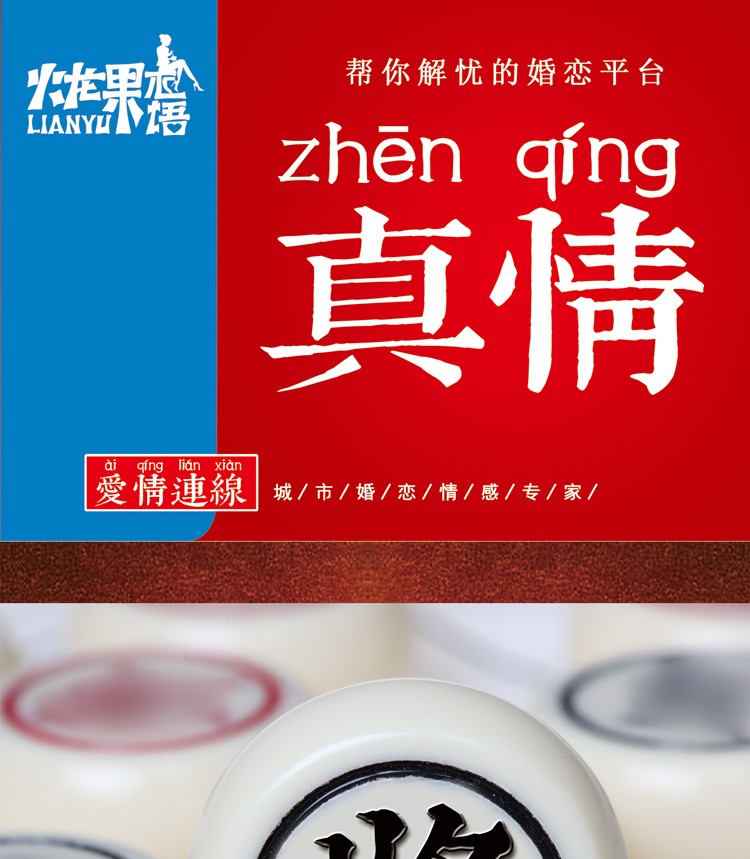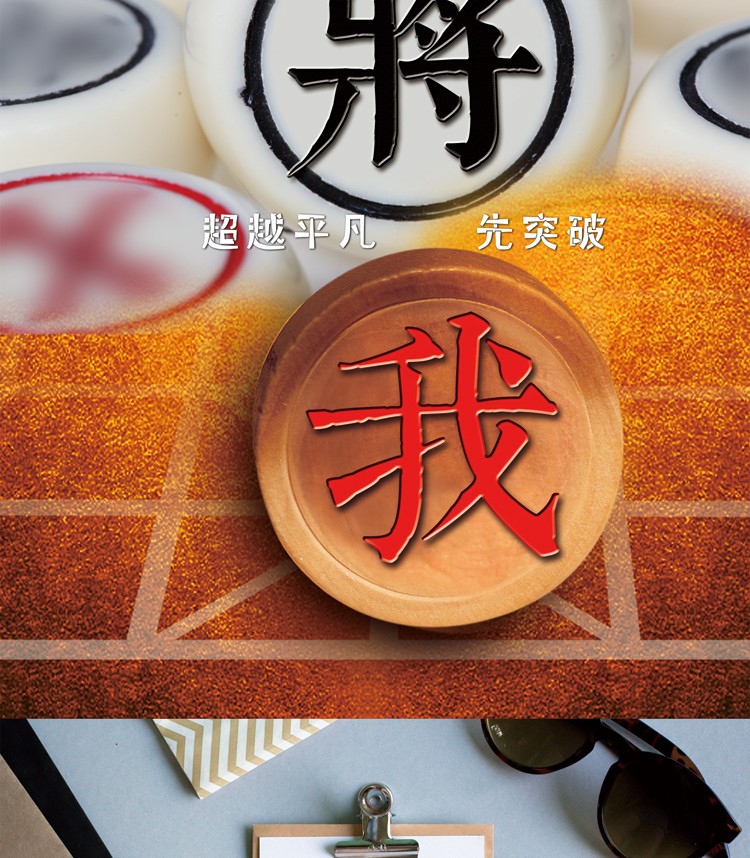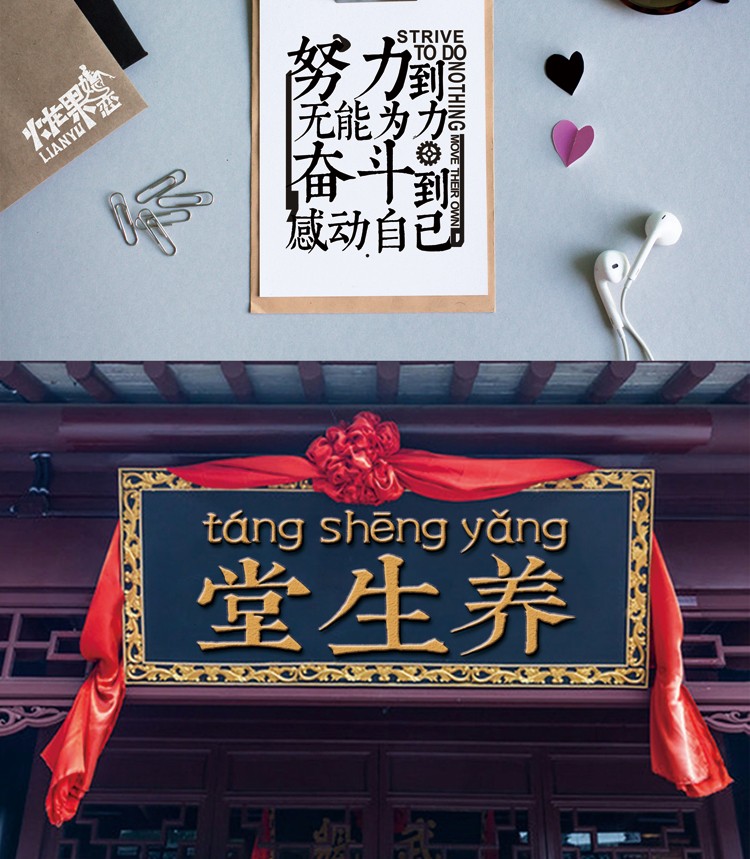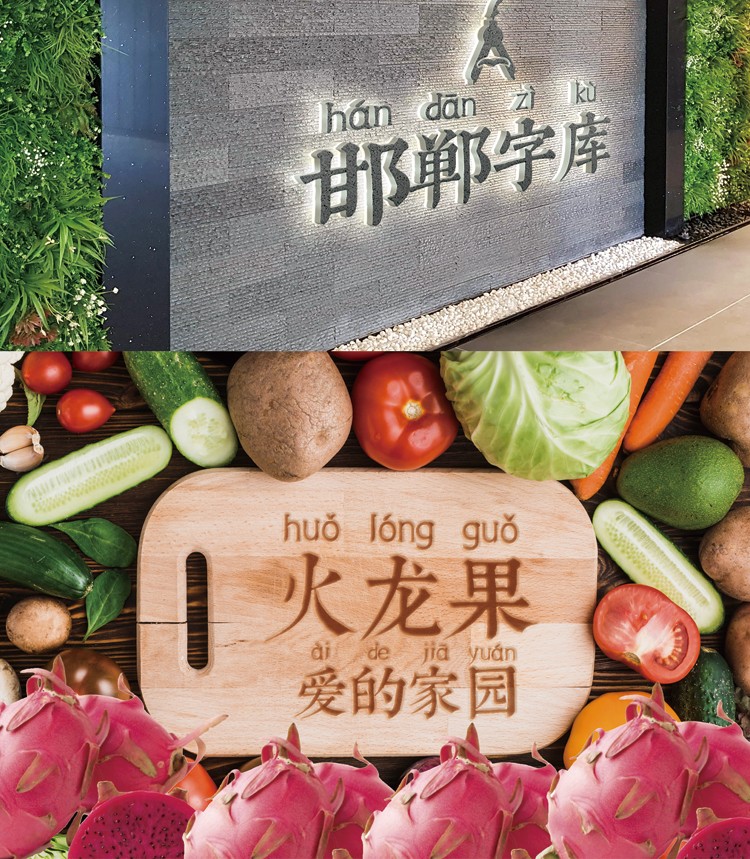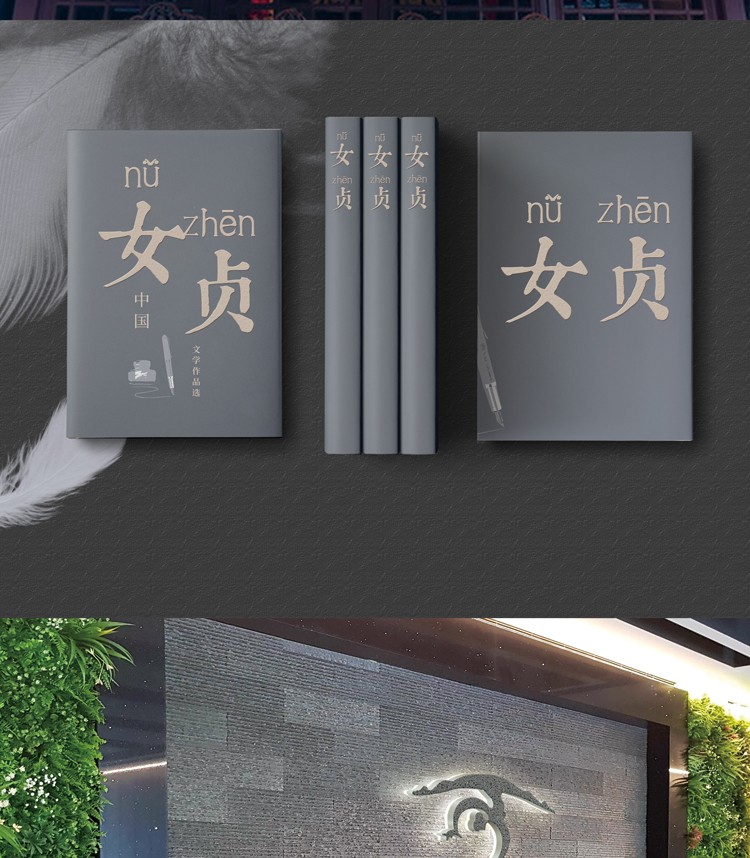
邯郸康熙字典注音体 详情页
字体名称: 邯郸康熙字典注
邯郸康熙字典注音体
邯郸康熙字典注音体字体下载邯郸康熙字典注音体【繁简精全47549字】
繁简精全共47549字
邯郸康熙字典注音体字体邯郸康熙字典注音体【繁简精全47549字】字库是一款让人赏心悦目、百看不厌的中文字体,适合各类广告和产品包装设计应用,字体大小79.38MB,格式为ttf字体,上传用户是邯郸字库,作者/版权方为韩绍杰